今回は実際にデザインで使えそうなかっこいい日本語のフリーフォントを厳選して紹介します。
そのままタイトル文字にできそうな、かっこいいフォントからかっこいいデザインに合いそうなフォントなどさまざまなフォントを集めました。
かっこいいフリーフォント【無料】
漢字も使えるかっこいいフォントを紹介します。
きなりゴシックmini
少しほっそりとした、角丸な明朝体です。まろやかで、軽い感じがする文字です。
なごみ極細ゴシック
極細のゴシックフォントです。無機質で清潔感のあるさっぱりしたフォントです。
バナナスリップ
ロンドB
直線で構成された文字はどこか懐かしいレトロな雰囲気です。
マキナス 4 シリーズ
マキナス 4 シリーズは【マキナス 4 Flat】と【マキナス 4 Square】の2種類のフォントが収録されています。
零ゴシック(フリーフォント)
インパクトMAX!
零ゴシック【ゼロゴシック】は、文字が割れているインパクトのあるフォントです。見出し・ロゴにピッタリのデザイン。
装甲明朝
横線が極細のステンシル体風の見出し向け明朝体です。 少し劣化したラフな雰囲気とミリタリーな雰囲気にも、男らしい格好良さにも マッチするフォントです。
かっこいいGoogle Fonts(グーグルフォント)
M PLUS 1p
メイリオに似ているフォントです。ふところが広くゆったりとした形状です。 デザインに使いやすいフォントです。
M PLUS Rounded 1c
M PLUS 1pの丸ゴシック体です。ウェイトは7種類
Noto Serif Japanese
クセがなく視認性にも優れたフォントです。Webサイトでもよく使われています。
Adobe Fontsのかっこいいフォント
Adobe Fontsに収録されているかっこいいフォントを紹介します。Adobe Fontsはひらがな、カタカナ、数字、アルファベット、漢字、記号すべて揃っています。
黒薔薇ゴシック
どこか懐かしさを感じるフォントです。
ABシグマ (Adobe Fonts)
丸みがあって、ゴシック体の印象ですが、文字に強弱ががある個性的な書体です。
読みやすい書体なので、長いタイトルでも使用できます。
いろいろと使えそうなフォントです。
AB 浪漫(Adobe Fonts)
懐かしさと不器用な印象のフォントです。独特な雰囲気を出せるフォントです。
あまり長いタイトルには合わないかも入れません。
ロンド B スクエア(Adobe Fonts)
柔らかく、少しコミカルな印象のフォントです。
特にひらがなが個性的です。見出しとしても使えそうです。
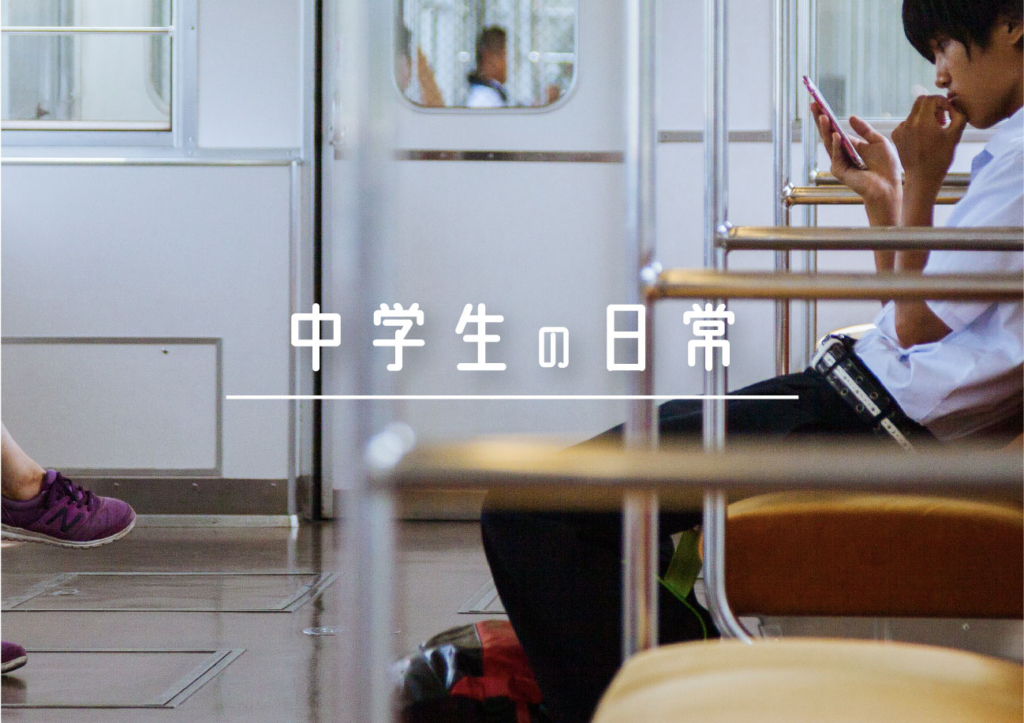
異世明(Adobe Fonts)
文字が少しずれている形のフォントです。特殊な印象を出したい時に使えるフォントです。
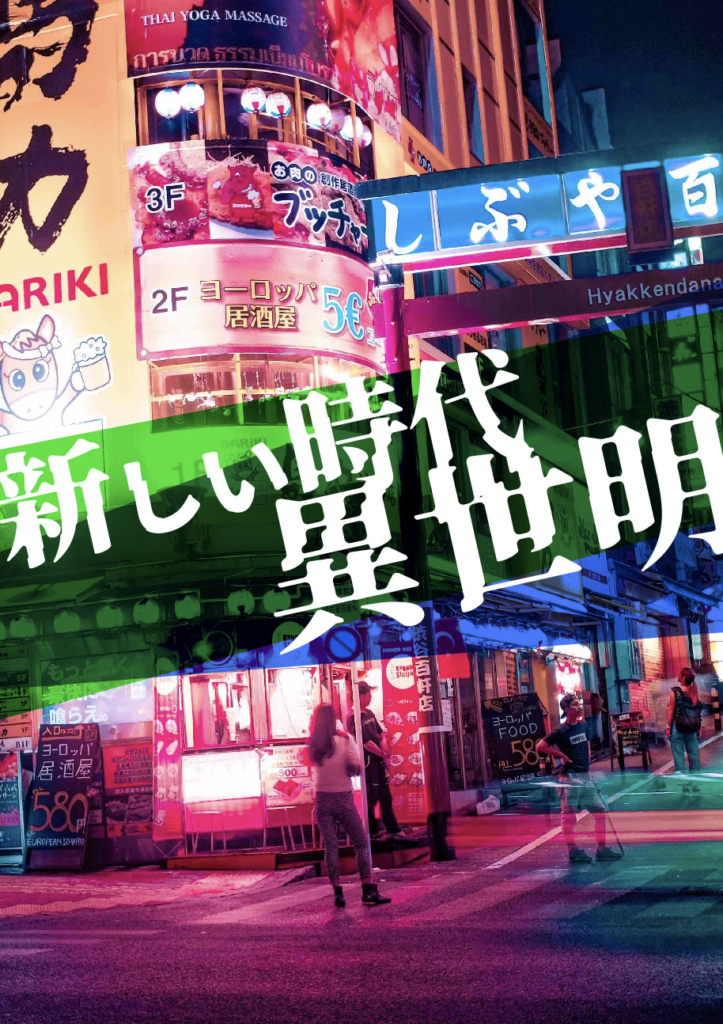
AB-くりっぷM(Adobe Fonts)
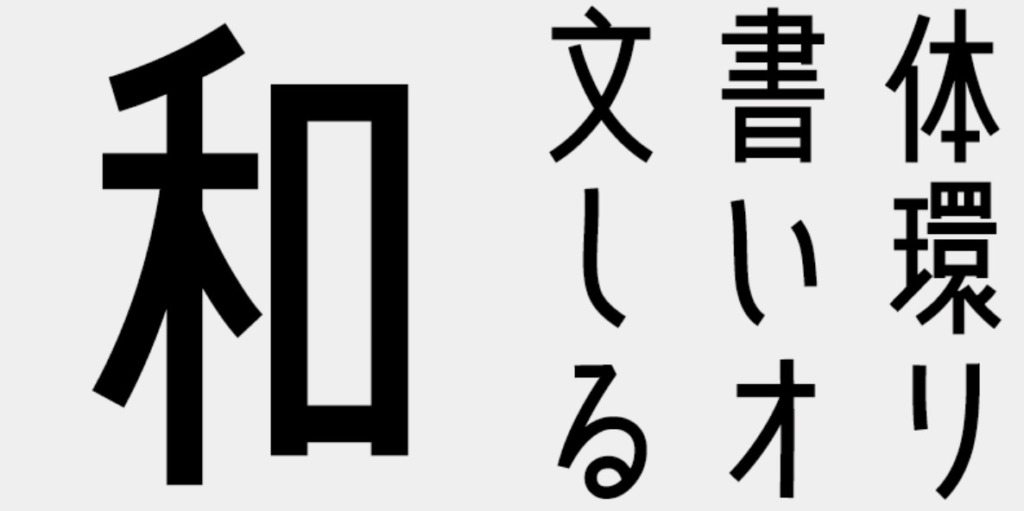
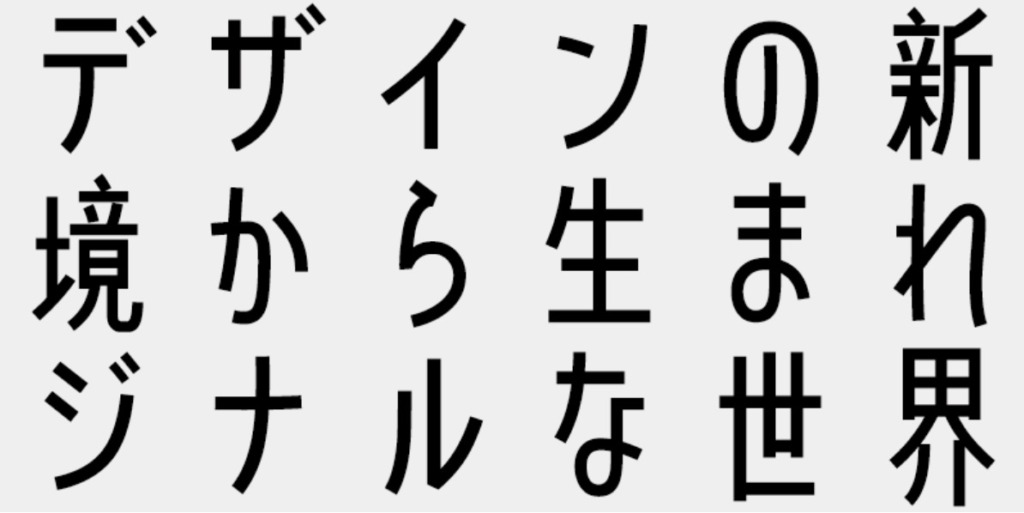
A-OTF UD新ゴ Pr6N
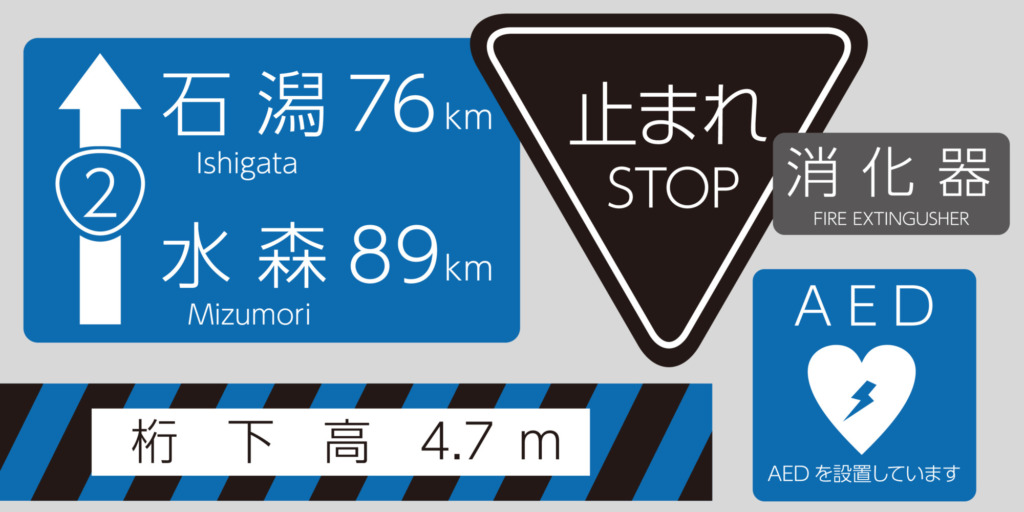
「UD 新ゴ」は、見やすい書体として評価の高く、個々の文字のわかりやすさを重視した字形をとりいれたユニバーサルデザイン書体です。
A-OTF UD新丸ゴ Pr6N